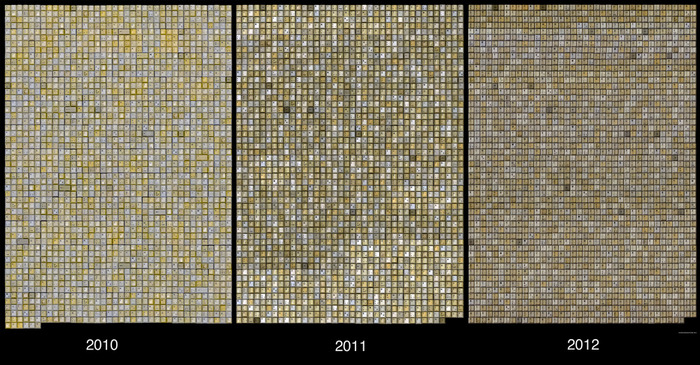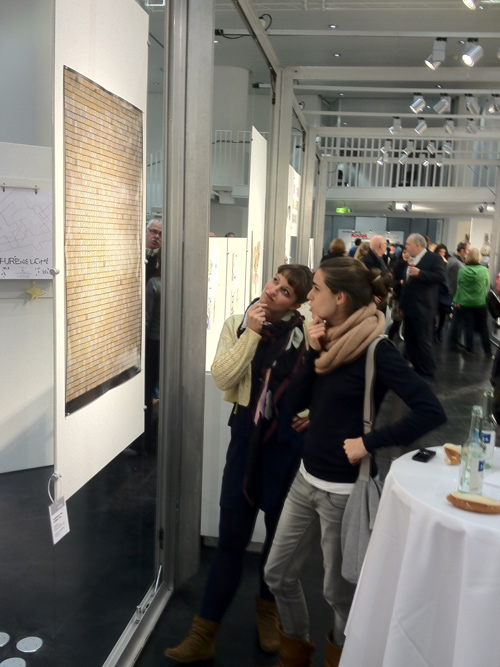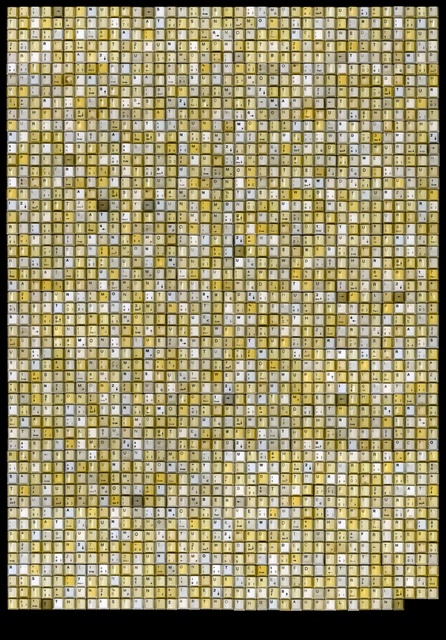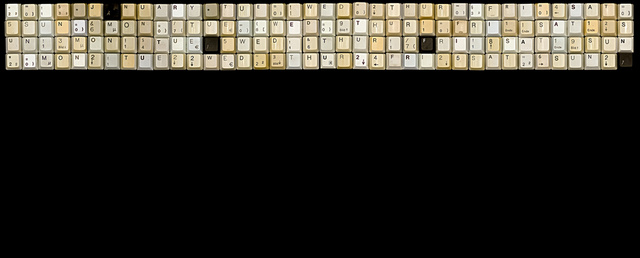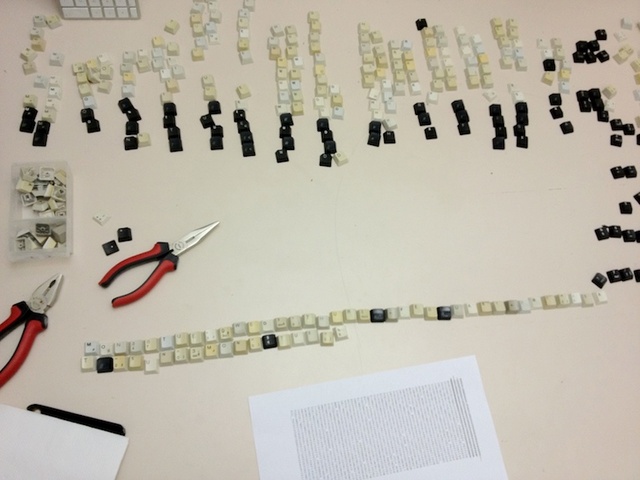
2013 Typographic Wall Calendar - aus Frankfurt - bei Kickstarter!
Die 2012 Edition des Typographic Wall Calendars hat sogar einen Preis in Stuttgart beim Gregor int. Calendar Award erhalten.
"…stunning reinterpretation of a calendar is a masterful example of how a designer can completely flip a genre signifier on its head. Geisler reimagines calendars in order to change the way we visualize time, and in turn, redefines what it means to save the date."-Mike McGregor, Kickstarter, NYC
"The more I look at this poster, the more in awe of it I am… it's a complete revision of the way we construct time, month by month, day by day. To see a year laid that way is somehow frightening and optimistic." -Elizabeth Kiefer, Editor at Fab, NYC
Worum geht es bei dem Projekt? Der “2013 Typographic Wall Calender” ist ein außergewöhnlich großer (70 x 100cm) Wandkalender der aus genau 2013 gebrauchten Tastaturtasten zusammengesetzt wird. Das Konzept wird seit 2009 von Harald Geisler kontinuierlich fortgeführt. Das Ergebnis wird jedes Jahr in Originalgröße(von 2013 Tastaturtasten) als Kunstdruck vervielfältigt.
Hier die 2013 Edition in groß:
Liest man die Tasten von links nach rechts so erschließt sich jeder einzelne Tag des Jahres. Die innere Struktur des gregorianische Kalender der seit 1582 “massgeblich” den westlich Kulturkreis bestimmt wird somit dekonstruiert und als Text rekonstruiert. Durch das zeigen von Tasten wird der Text jedoch nicht direkt rekonstruiert. Die Taste liegt einen Moment vor dem Erscheinen des Textes. Sie will erst betätigt werden bevor der Text buchstäblich in Erscheinung tritt.
Ist dies überhaupt ein Kalender? Was passiert wenn ich eine Taste drücke? Ist es vielleicht eine Zeitmaschine? Könnte man so weit gehen und sagen das alle Kalender etwas zeit-maschinenhaftes an sich haben?
Hier ein Bild der Versionen von 2010, 2011 und 2012 Version: